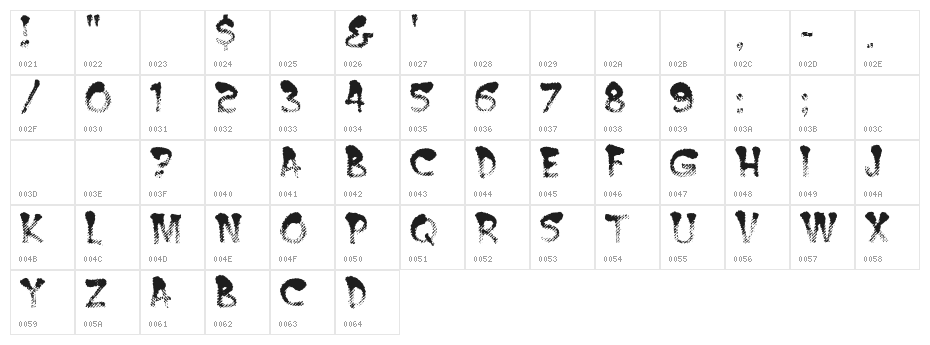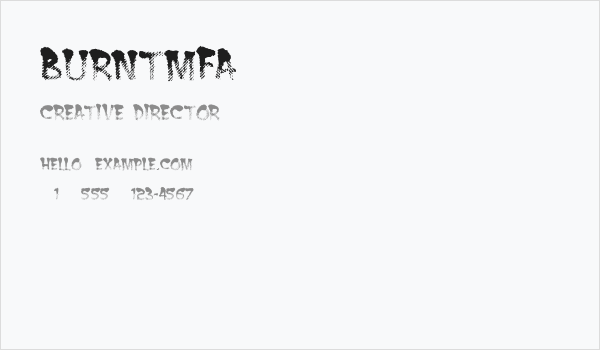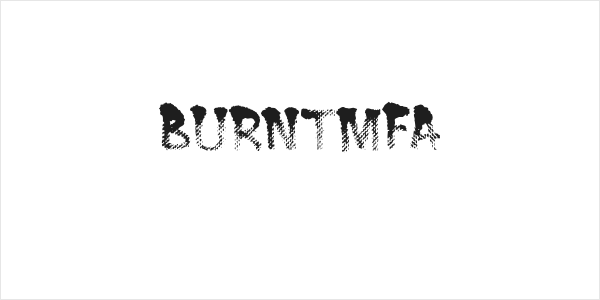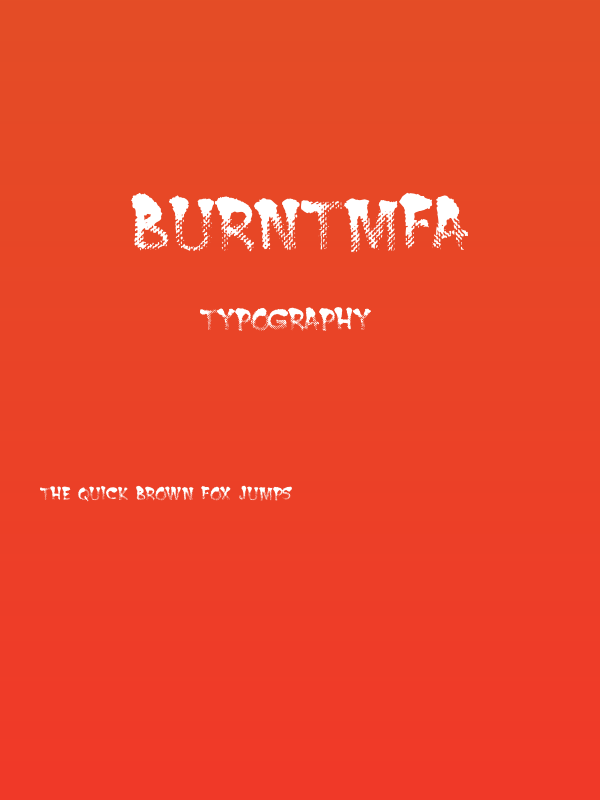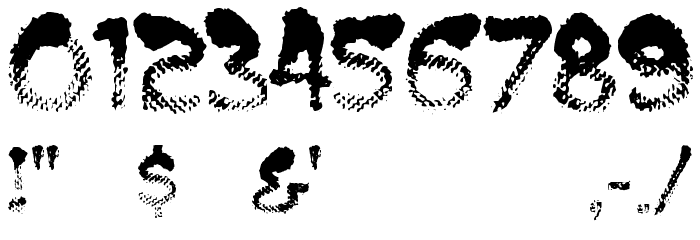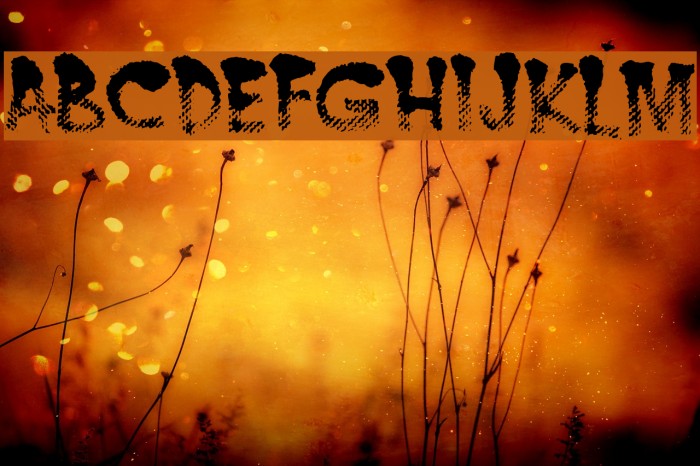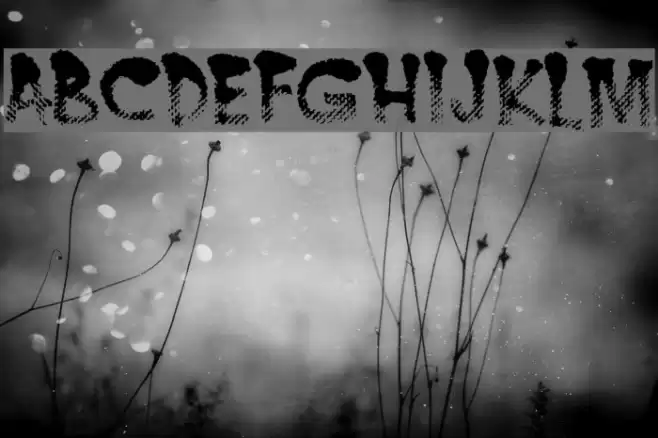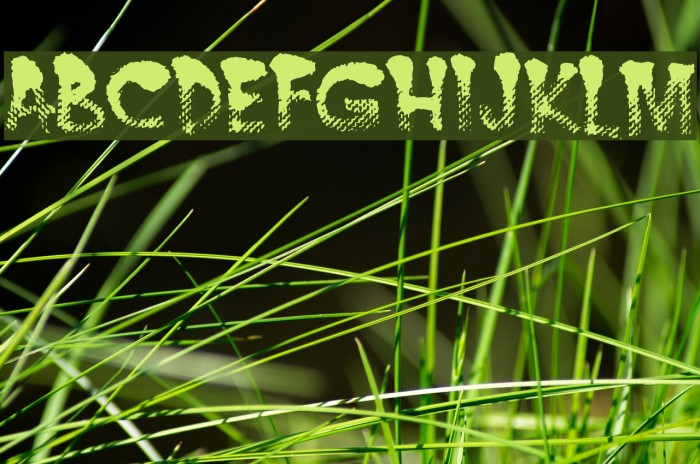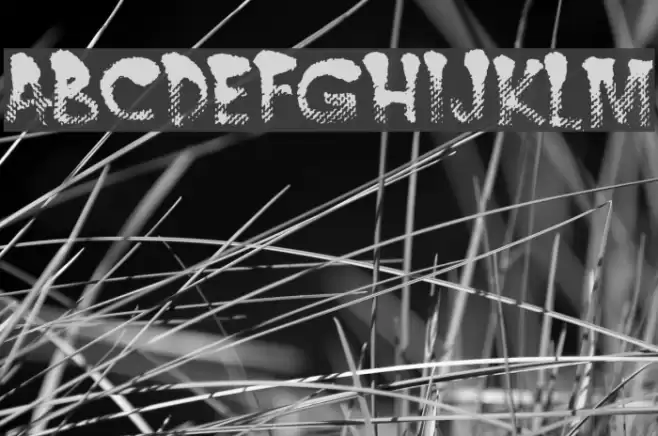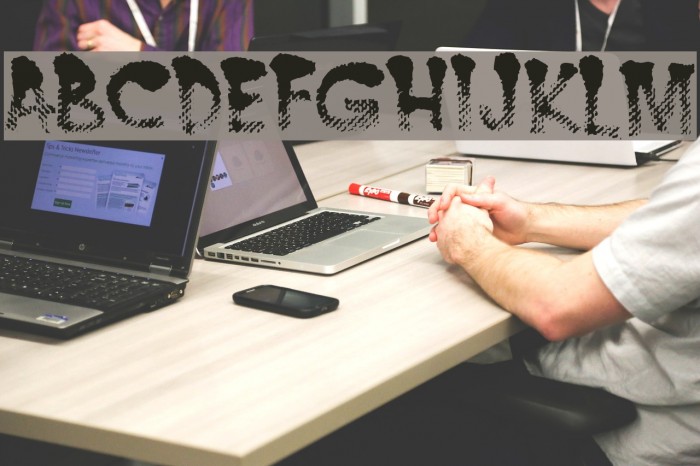
BurntMFA Font
| Projetos propostos | Ideal for projects requiring a rugged, edgy look such as posters, album covers, or branding for extreme sports. |